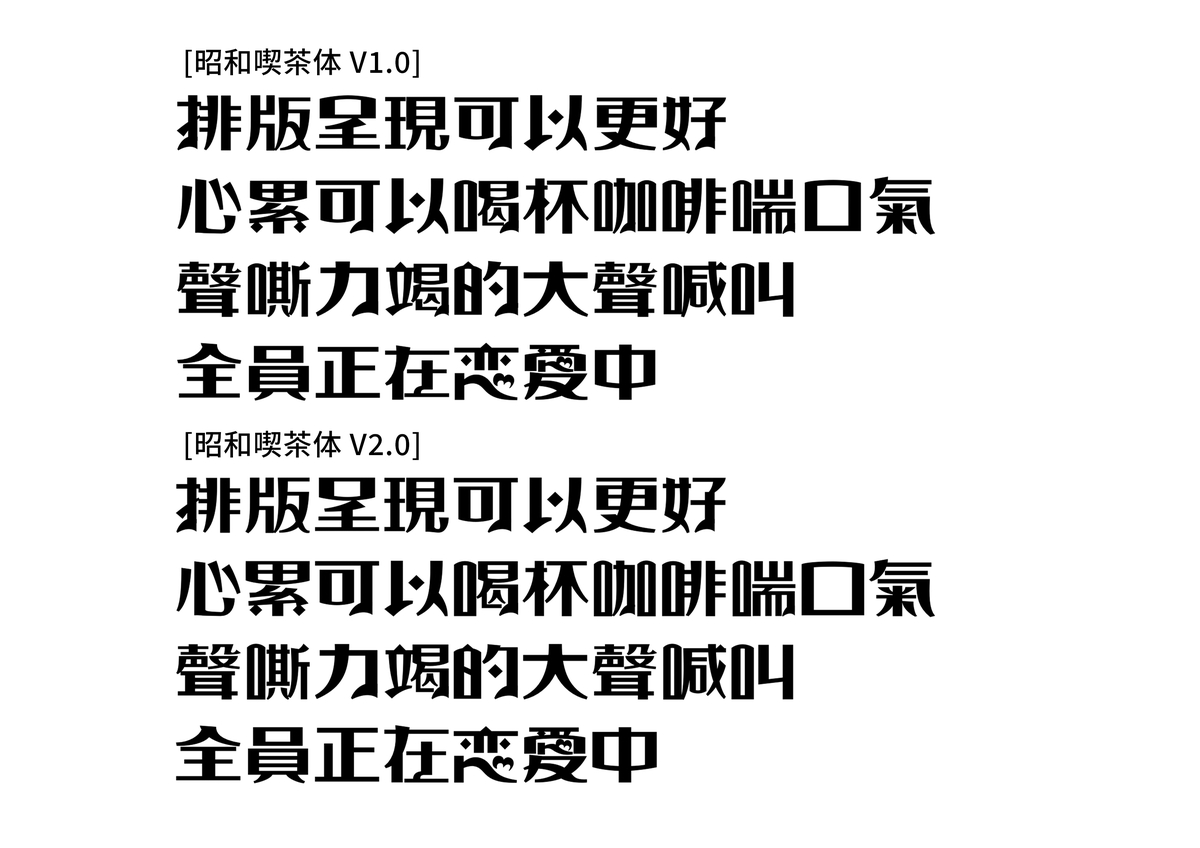
《昭和喫茶體》|【復古昭和●大正浪漫】沖一壺懷舊的咖啡,寫一首溫柔的詩句,讓我們一起浪漫的回到過去
計畫更新 #3昭和喫茶体-重大時程&改良調整公告
但由於團隊內部討論後,希望能再改良使用上的體驗,例如灰度,一致性,視覺穩定度,也更凸顯字體的細節(如負空間),因此決定延後整體發布時程。
[改良內容]
-進一步調整字體平均灰度
-修正上下緣落差太大,導致視覺跳動的問題
-檢查並確保造型及組件一致
-改善單字造型與負空間平衡